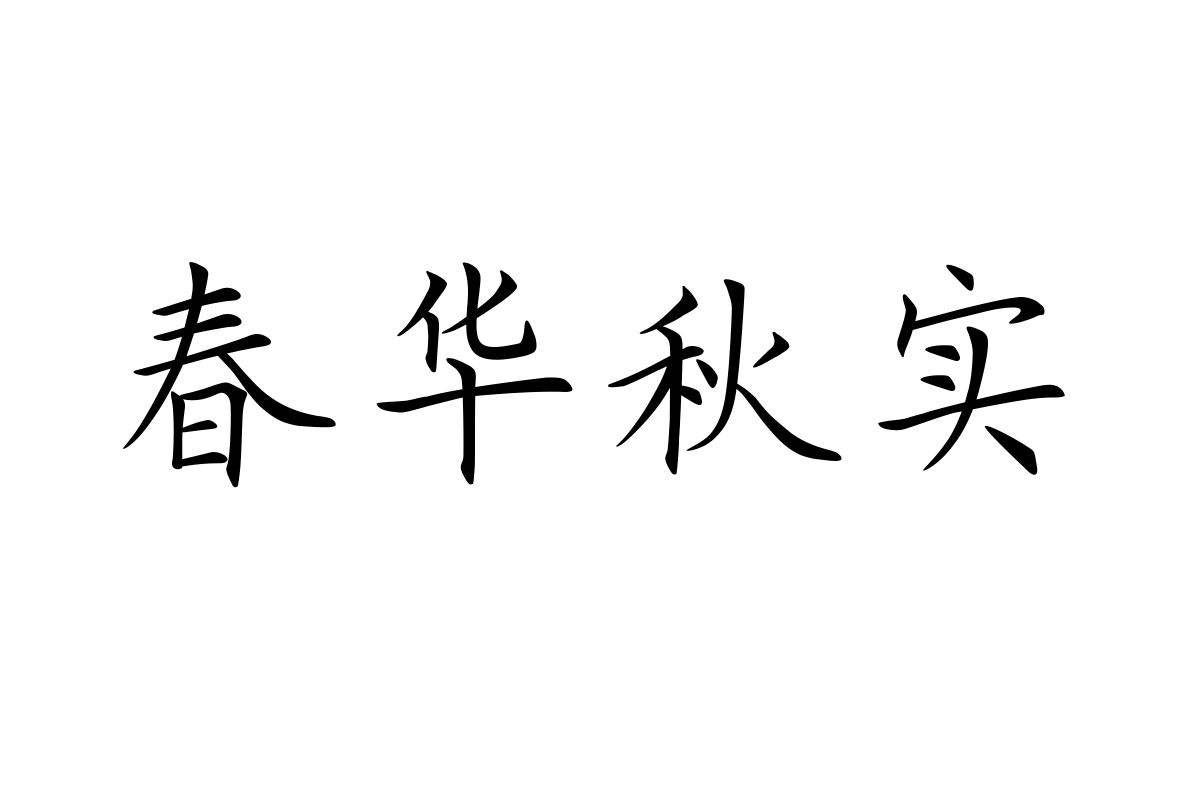
三极书楷简体字体是一款由三极科技有限公司开发的中文字体,具有简洁、清晰的特点。这款字体适用于各种印刷品和电子屏幕显示,如书籍、报纸、杂志、广告等。
三极书楷简体字体的字形结构紧凑,笔画流畅,易于阅读和书写。它采用现代设计手法,将传统书法元素与现代审美相结合,既保留了汉字的传统韵味,又符合现代人的审美习惯。
三极书楷简体字体的主要特点如下:
1. 字形结构紧凑:三极书楷简体字体采用简洁的设计手法,使字形更加紧凑,有利于提高阅读和书写的效率。
2. 笔画流畅:该字体的笔画线条流畅自然,没有过多的装饰性笔画,使得整个字体看起来更加简洁大方。
3. 易于识别:三极书楷简体字体的字形结构清晰明了,无论是在印刷品还是电子屏幕上,都能快速地被读者识别出来。
4. 适合多种场景:这款字体适用于各种印刷品和电子屏幕显示,如书籍、报纸、杂志、广告等,能够满足不同场景的需求。
总之,三极书楷简体字体是一款实用性强、适用范围广的中文字体,适用于各种印刷品和电子屏幕显示,是设计师和印刷厂常用的一款字体。